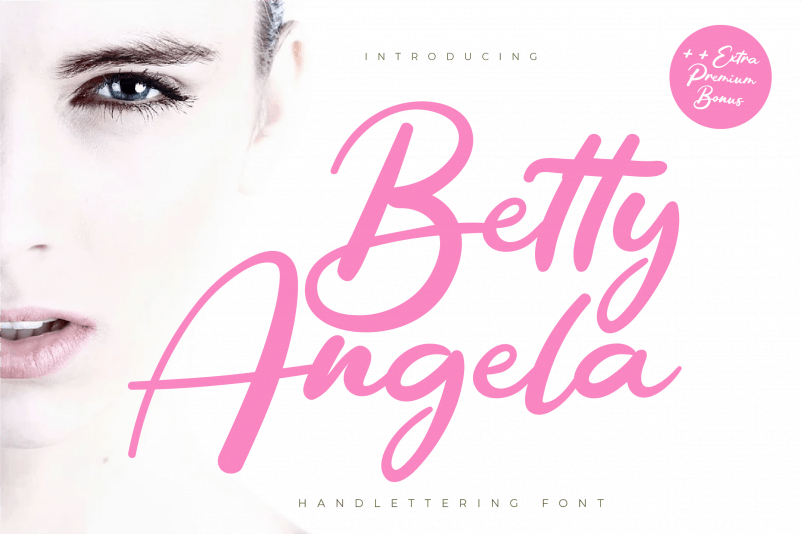
A Betty Angel Script Font é uma delícia para os designers que buscam trazer um toque delicado e sofisticado a seus projetos digitais. Com sua elegância única, essa fonte script é perfeita para criar designs únicos para convites de casamento, cartões de agradecimento, mensagens personalizadas e até mesmo em logomarcas ou cartões de visita. Suas linhas fluidas criam um ar elegante que encaixa-se naturalmente tanto no estilo mais tradicional quanto no contemporâneo, tornando-a uma fonte versátil para projetos variados. Ideal para os designers que buscam trazer um toque de personalidade e requinte em seus trabalhos, a Betty Angel Script Font é uma opção perfeita para aqueles que desejam destacar-se na comunidade gráfica brasileira com um design único e sofisticado.